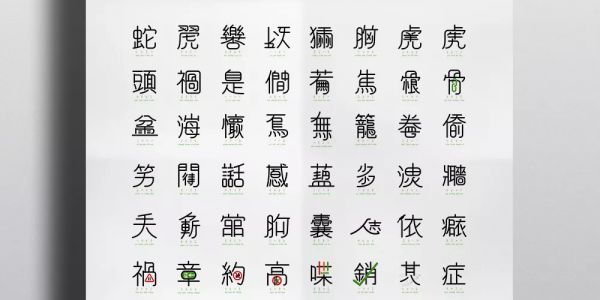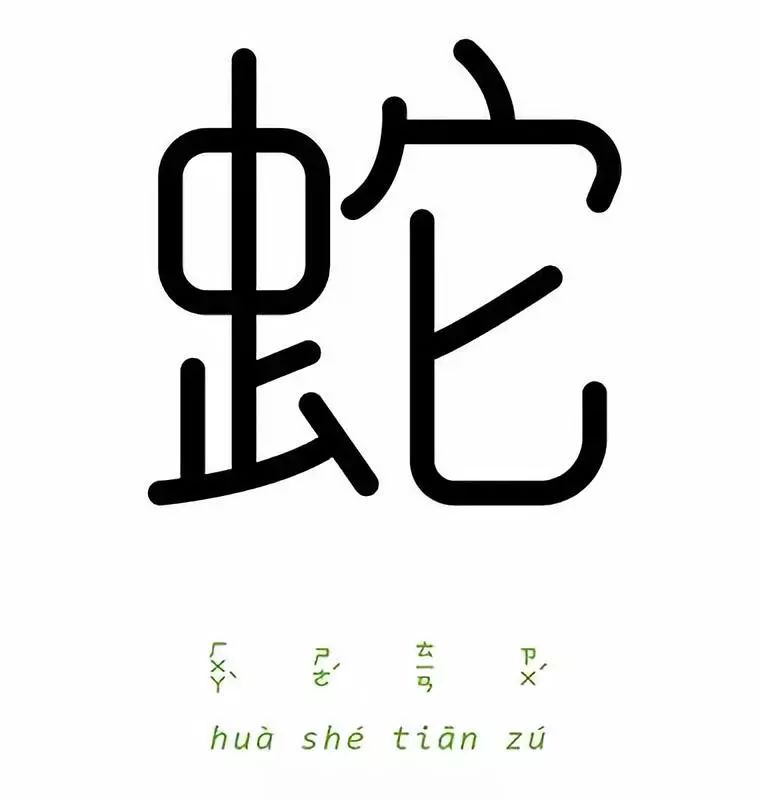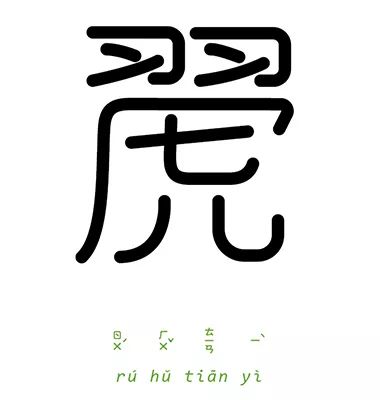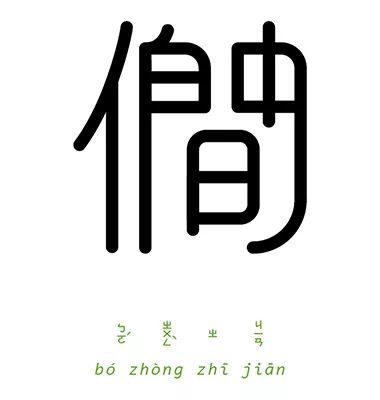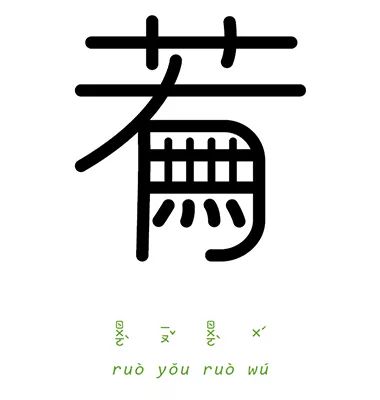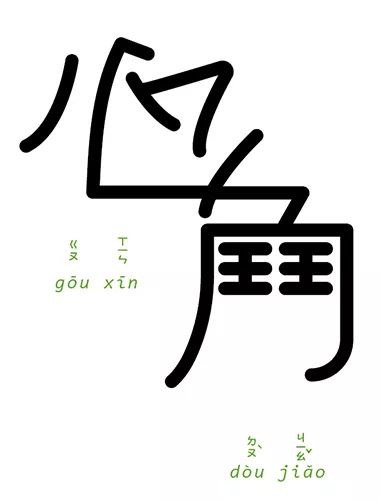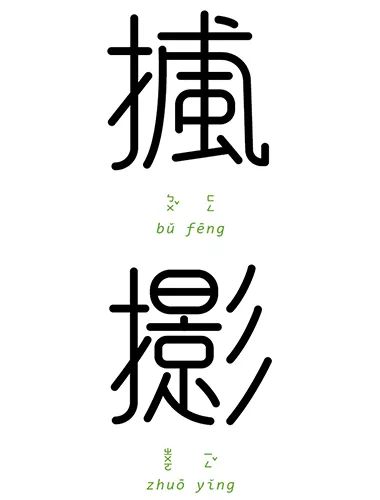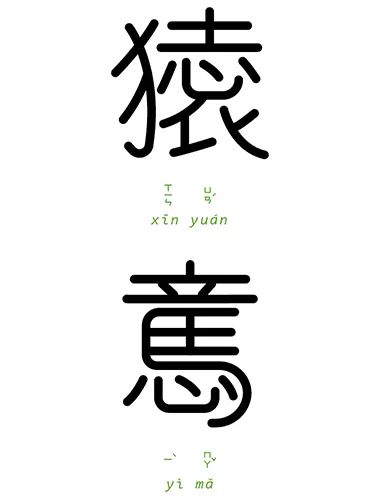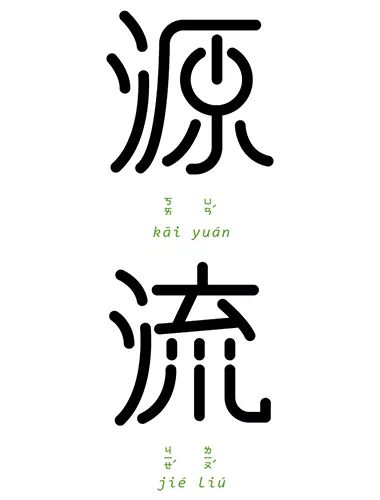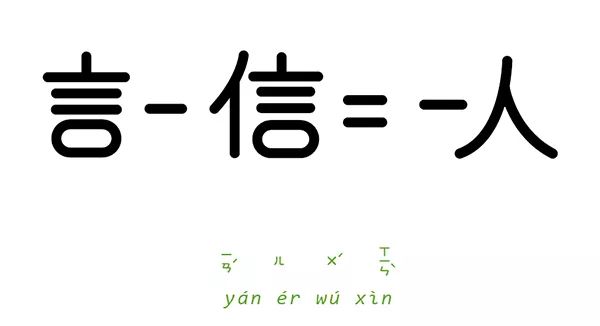
一字一成语,这样的汉字设计非常烧脑了!
成语是一种独特的语言形式,表达固定的意义,常带有历史含故及哲理,大多以四个字组成。
“字以为释”成语实验计划,是来自台湾的设计师Chen Chiao-Yu的作品。以成语为主题的字体创作,将文字结合文字创造出新字或者结合符号,完成一系列的创作。
以下有67个字体设计,同时也是67个成语,不看答案的话,你能猜出几个呢?
画蛇添足
如虎添翼
苦中作乐
以牙还牙
两小无猜
胸有成竹
羊入虎口
九牛二虎
祸从口出
自以为是
伯仲之间
若有若无
牛头马面
恨之入骨
骨肉相连
改头换面
上山下海
百感交集
话中有话
待字闺中
笑里藏刀
偷天换日
开卷有益
无中生有
笼中之鸟
一石二鸟
耿耿于怀
小鸟依人
崭露头角
隔墙有耳
官官相护
人各有志
囊空如洗
一手遮天
雪上加霜
积少成多
青出于蓝
对症下药
虚有其表
一笔勾销
高不可攀
喋喋不休
不约而同
出口成章
祸不单行
断袖之癖
火上加油
祸从口出
倾盆大雨
正中下怀
虚左以待
风前残烛
胸无点墨
黑白分明
一哄而散
甜言蜜语
雾里看花
蝇头小利
双管齐下
勾心斗角
捕风捉影
心猿意马
开源节流
言而有信
刮目相看
隔行如隔山